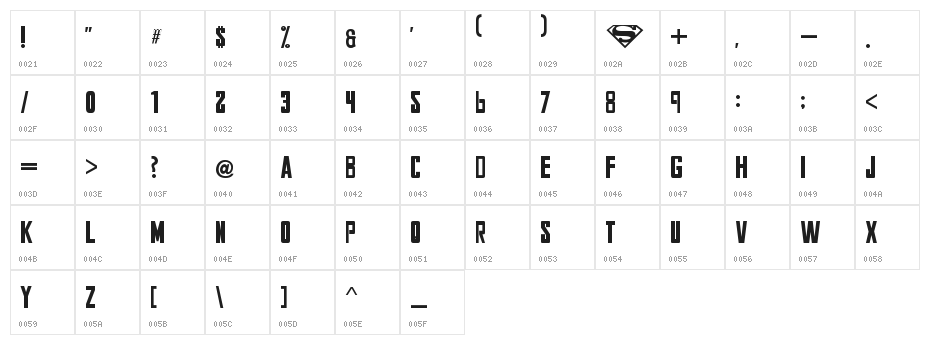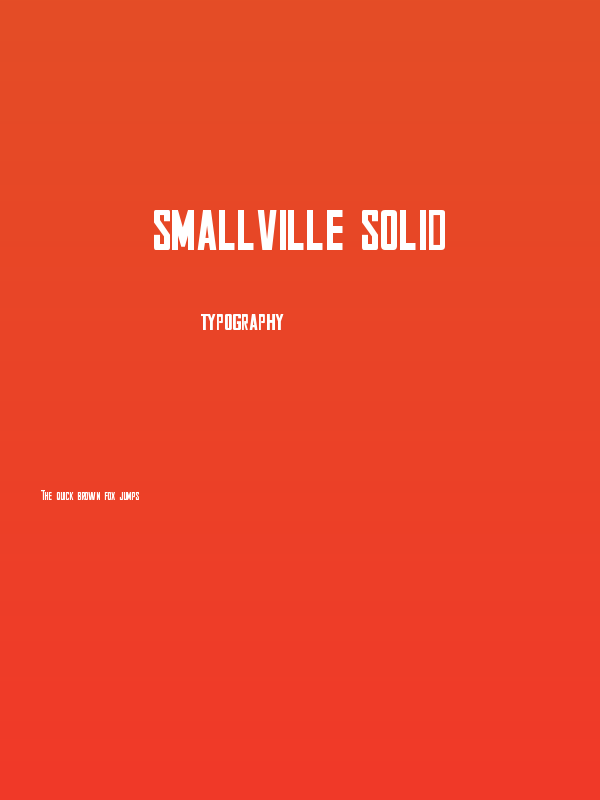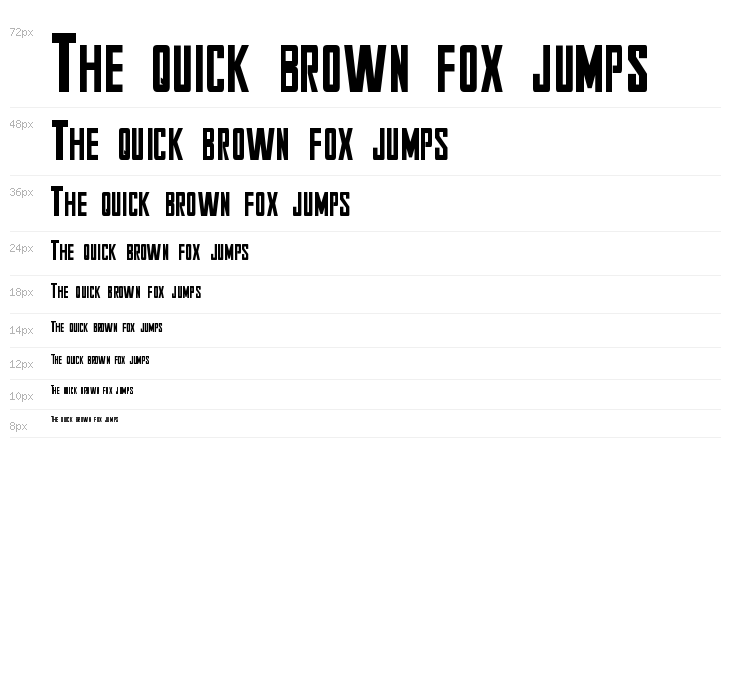
Smallville Solid Font
| Progetti proposti | Ideal for comic book covers, superhero-themed posters, branding for entertainment media, and dynamic logo designs. |